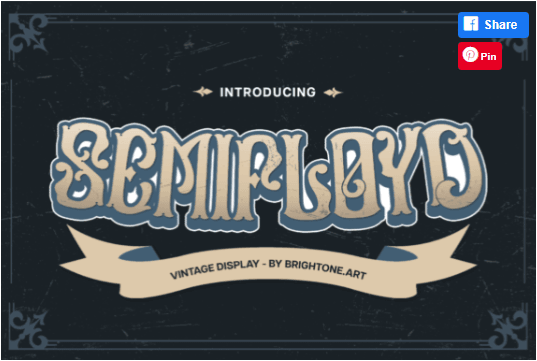
Шрифт Semifloyd
Semifloyd Font
Semifloyd — классический декоративный шрифт с засечками с хорошим стилем и уникальным оттенком. Этот шрифт включает в себя:
Шрифт Semifloyd подходит для любых целей: для написания логотипа, этикетки, упаковки, наклейки, брендинга и многого другого.